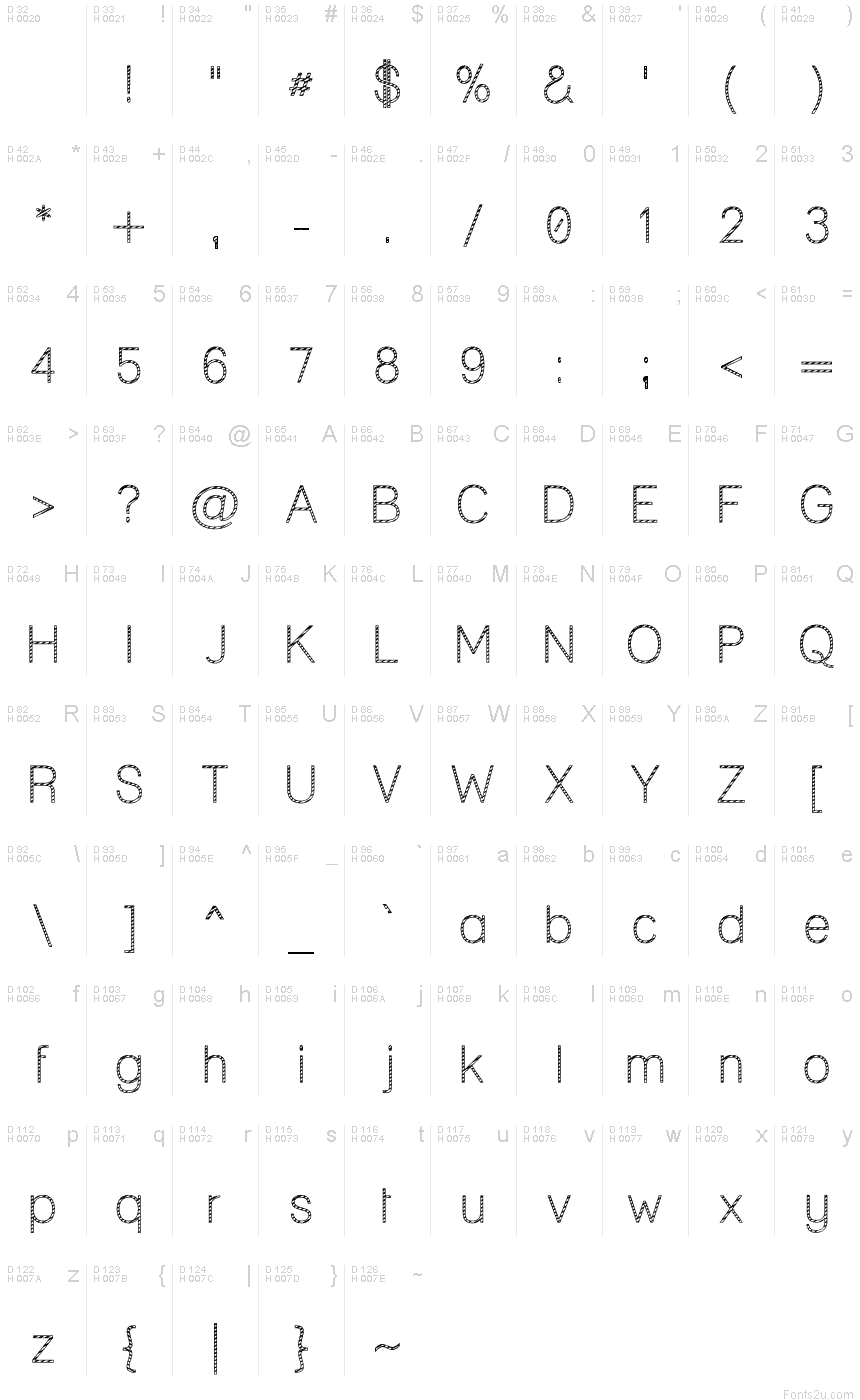
خط Cane Lane Light من GeM هو خط عرض زخرفي مجاني يضفي لمسة عصرية على الحروف عبر خطوط مرحة تشبه أعواد الحلوى. يمنح الهيكل المفرغ للخط طابعاً هوائياً خفيفاً، بينما تضفي الخطوط المائلة ملمساً «مقرمشاً» يشبه السكر، مما يضفي أجواء احتفالية فورية دون أن تبدو ثقيلة. يتميز الخط بوضوح عالٍ عند استخدامه بأحجام متوسطة إلى كبيرة، مما يجعل الخطوط الملتوية تبدو حادة وأنيقة بعيداً عن التكدس.
باستخدام Cane Lane Light، يمكنك إضفاء طابع احتفالي مريح على بطاقات المعايدة، ودعوات الحفلات، وتغليف المخبوزات، وملصقات الأطفال، ولوحات المتاجر الموسمية، والمنشورات المبهجة على وسائل التواصل الاجتماعي. هذا الخط المجاني يتألق حقاً عندما يُمنح مساحة كافية للتنفس؛ لذا اجعله العنوان الرئيسي وقم بإقرانه بخط بلا زوائد (sans serif) بسيط للنص الأساسي لتسليط الضوء على تصميم الخطوط الجذاب.